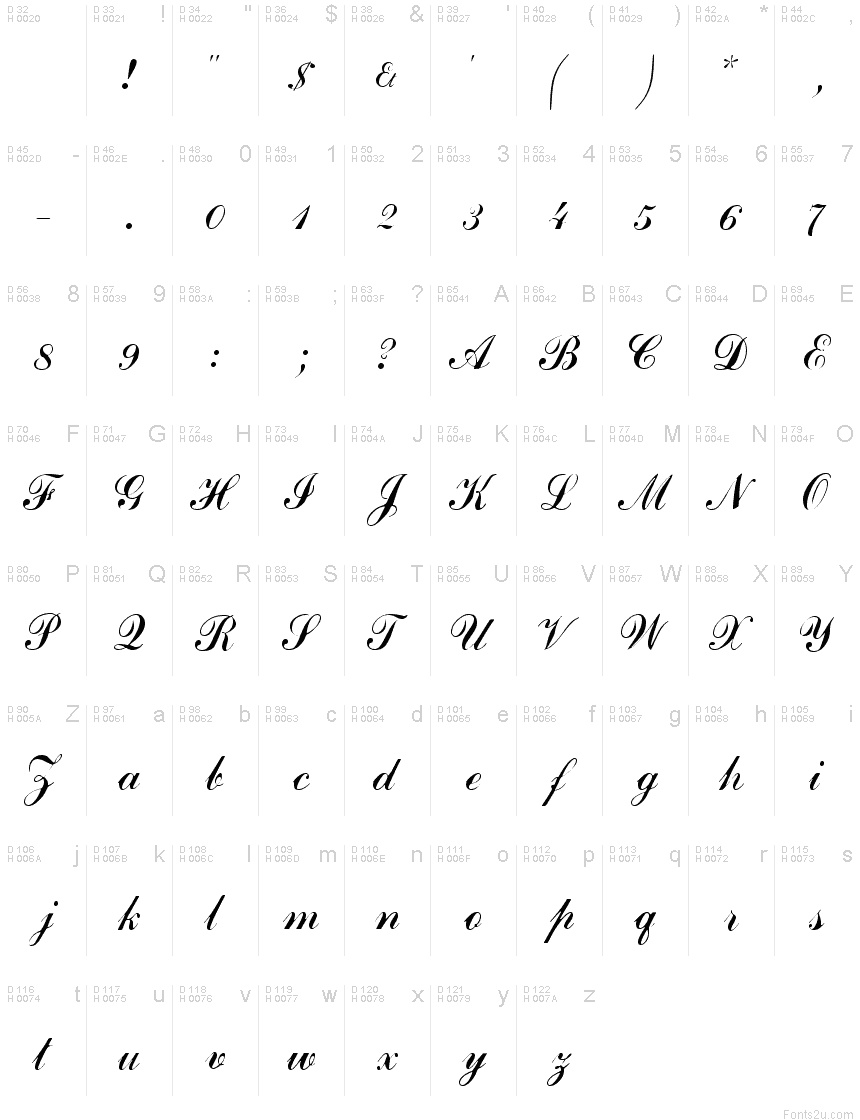
Commercial Script 3 to darmowy font kaligraficzny, który łączy formę odręcznego pisma z dopracowanym, komercyjnym sznytem. Litery dynamicznie suną naprzód dzięki eleganckim, pochylonym pociągnięciom, grubym liniom i delikatnym łączeniom – jakby zostały nakreślone dobrze napełnionym piórem. Rytm jest płynny i harmonijny, nadając słowom wdzięczną, luksusową teksturę, która nie sprawia wrażenia sztywnej.
Commercial Script 3 doda wyrafinowanego dramatyzmu zaproszeniom ślubnym, ekskluzywnym opakowaniom, logotypom butikowym, certyfikatom czy klasycznym plakatom. Ten darmowy font świetnie wygląda w dużym rozmiarze, gdy jego długie pociągnięcia mogą w pełni wybrzmieć. Połącz go z czystym, geometrycznym fontem bezszeryfowym w tekście głównym, aby podkreślić jego błyszczący, wyrafinowany charakter.